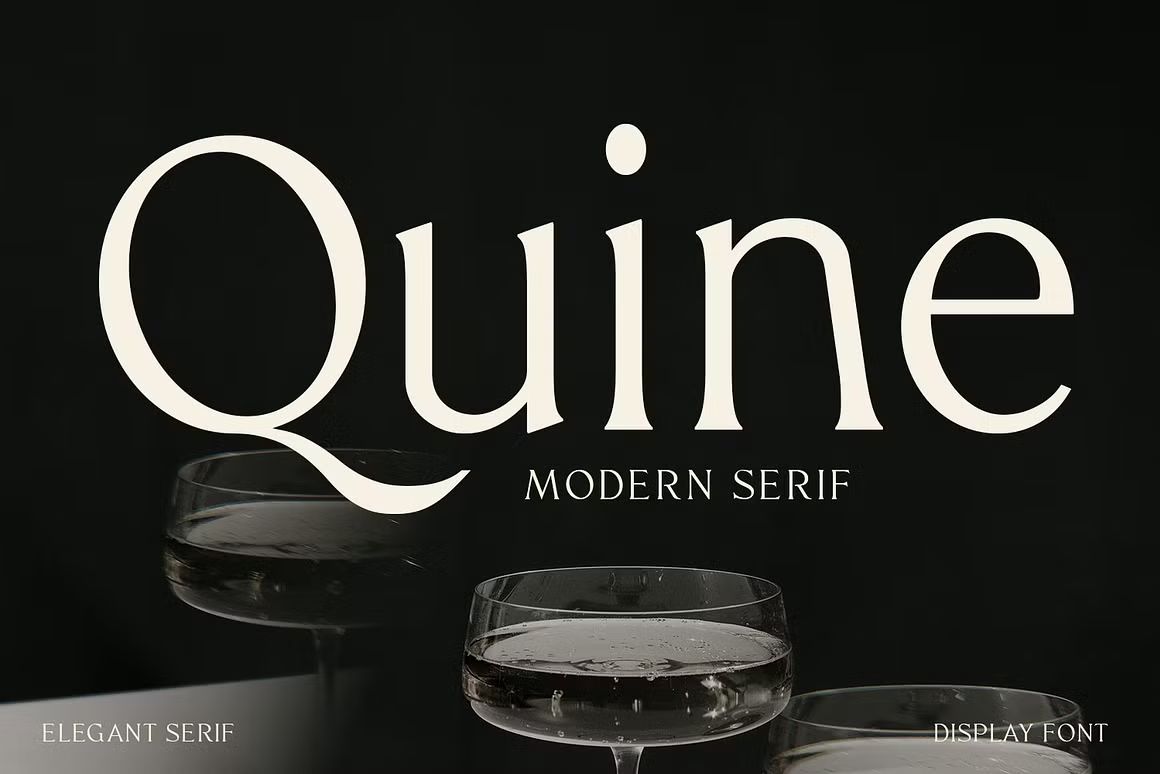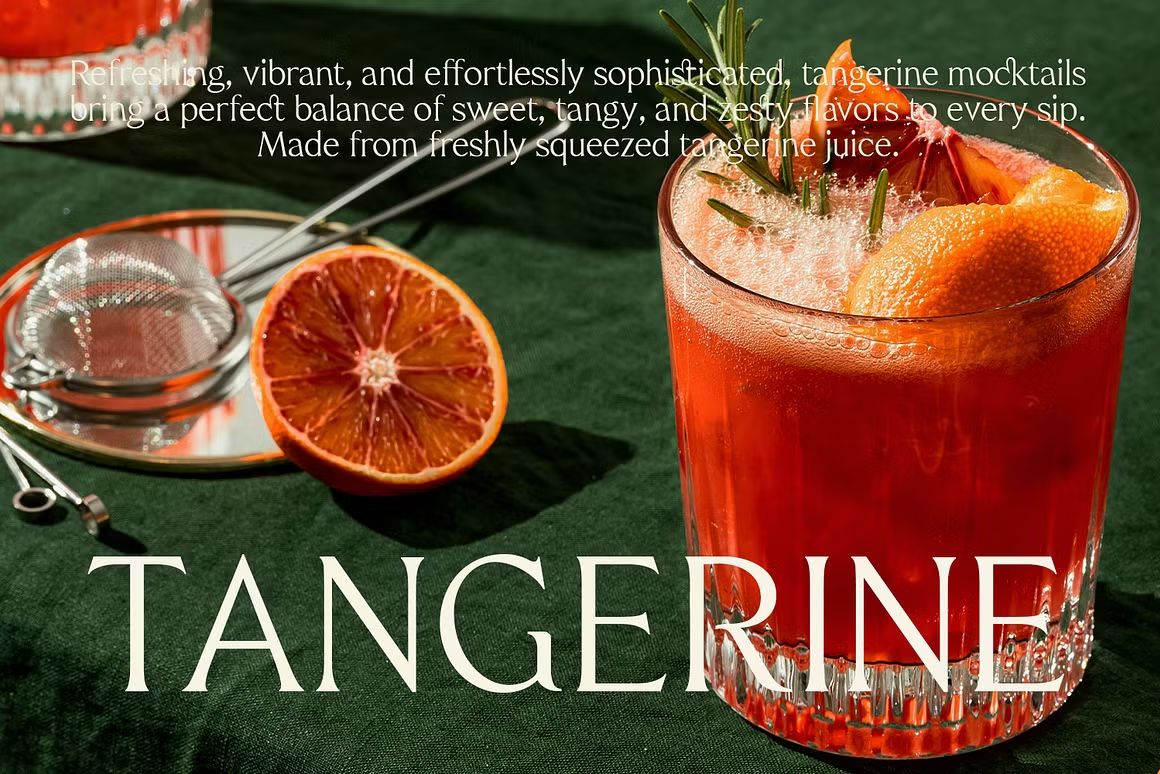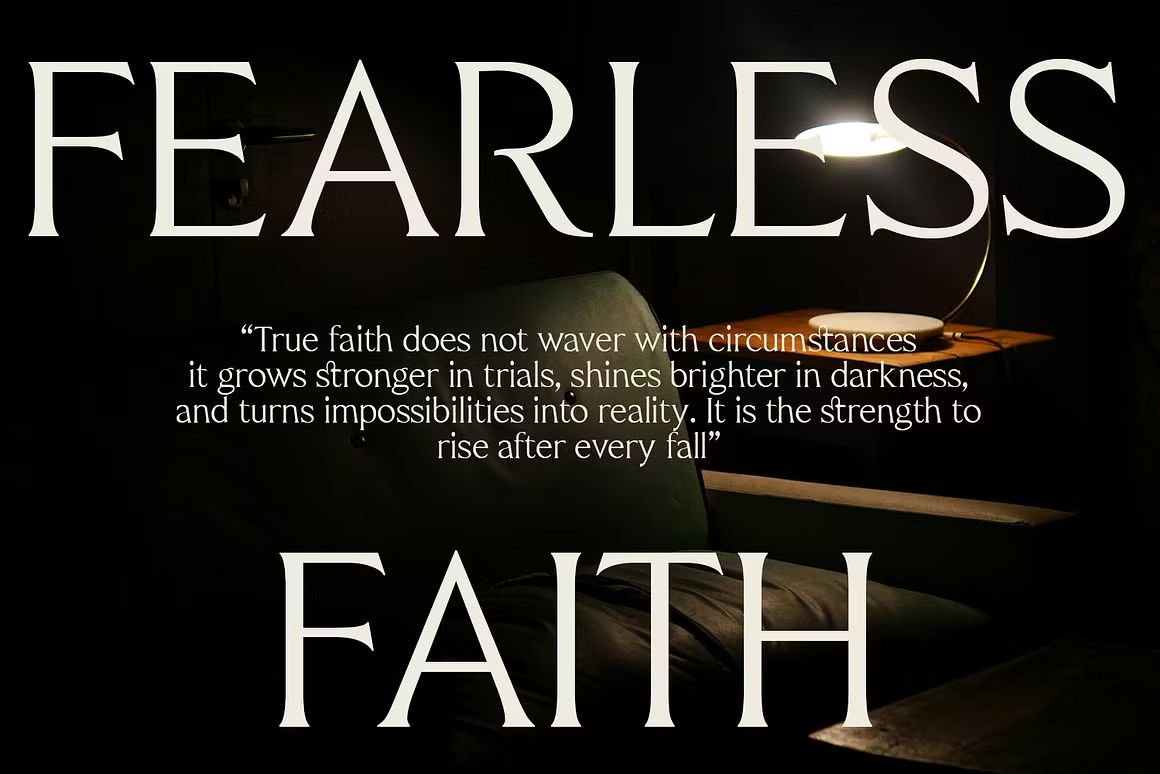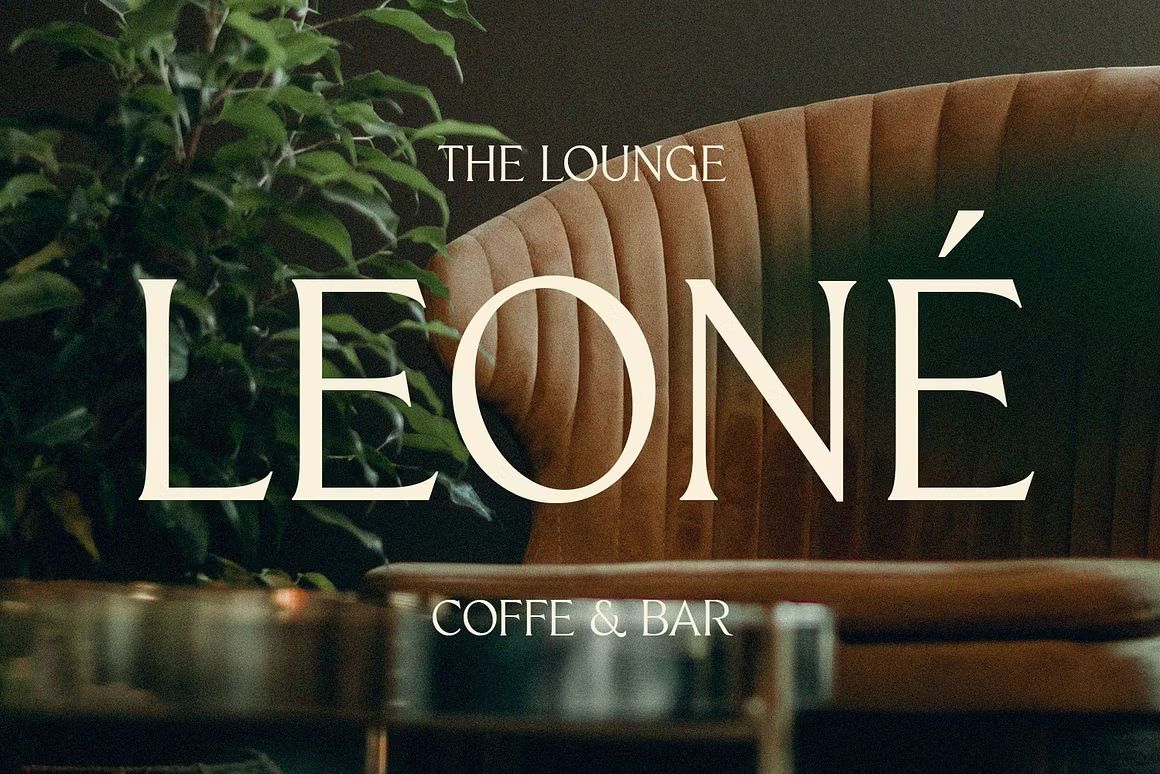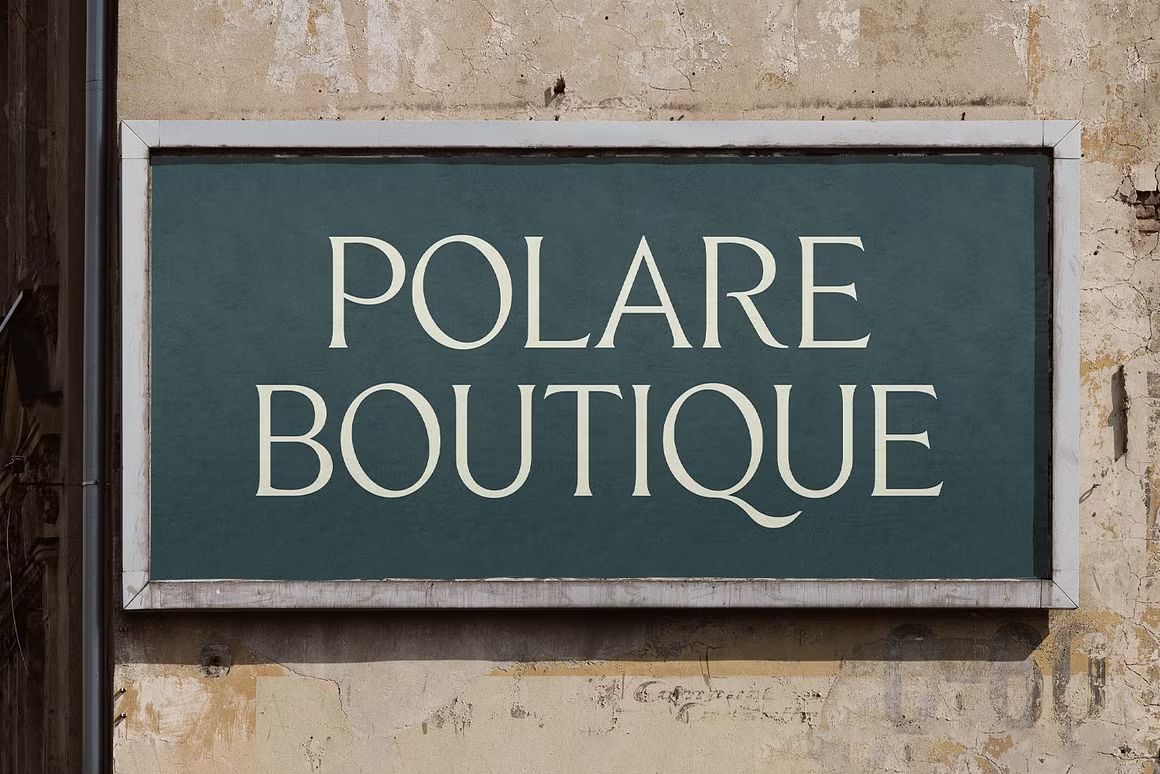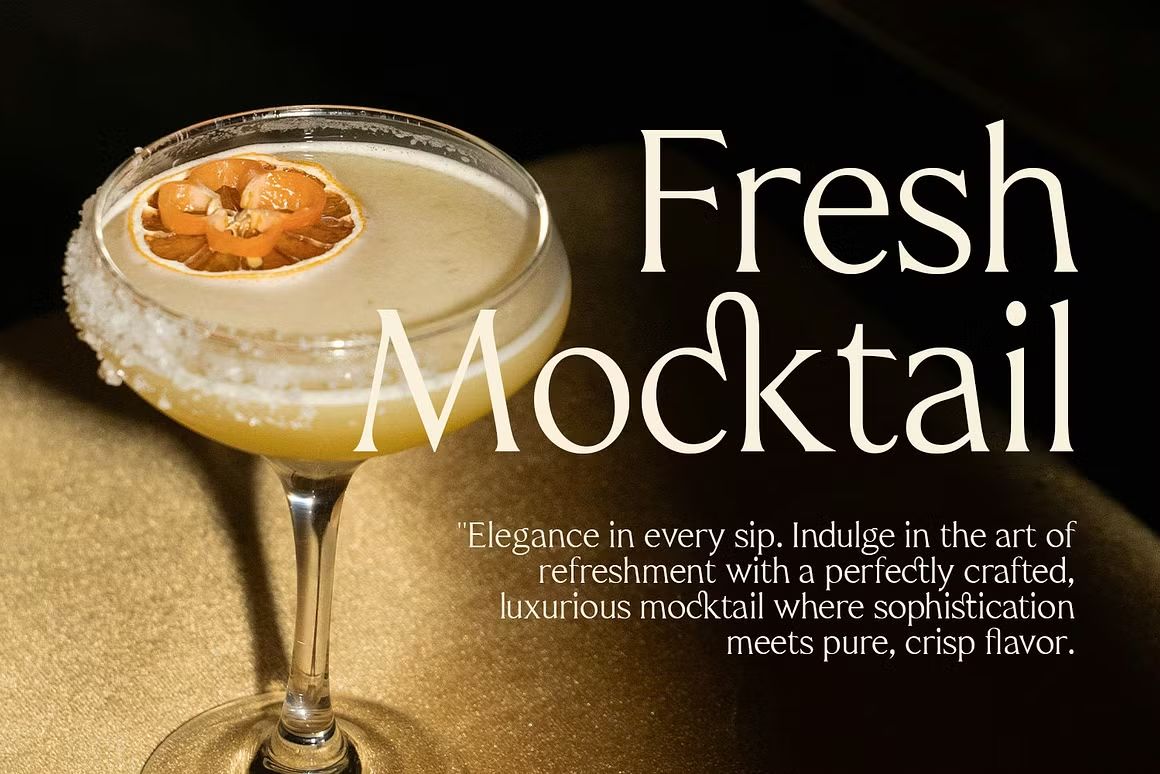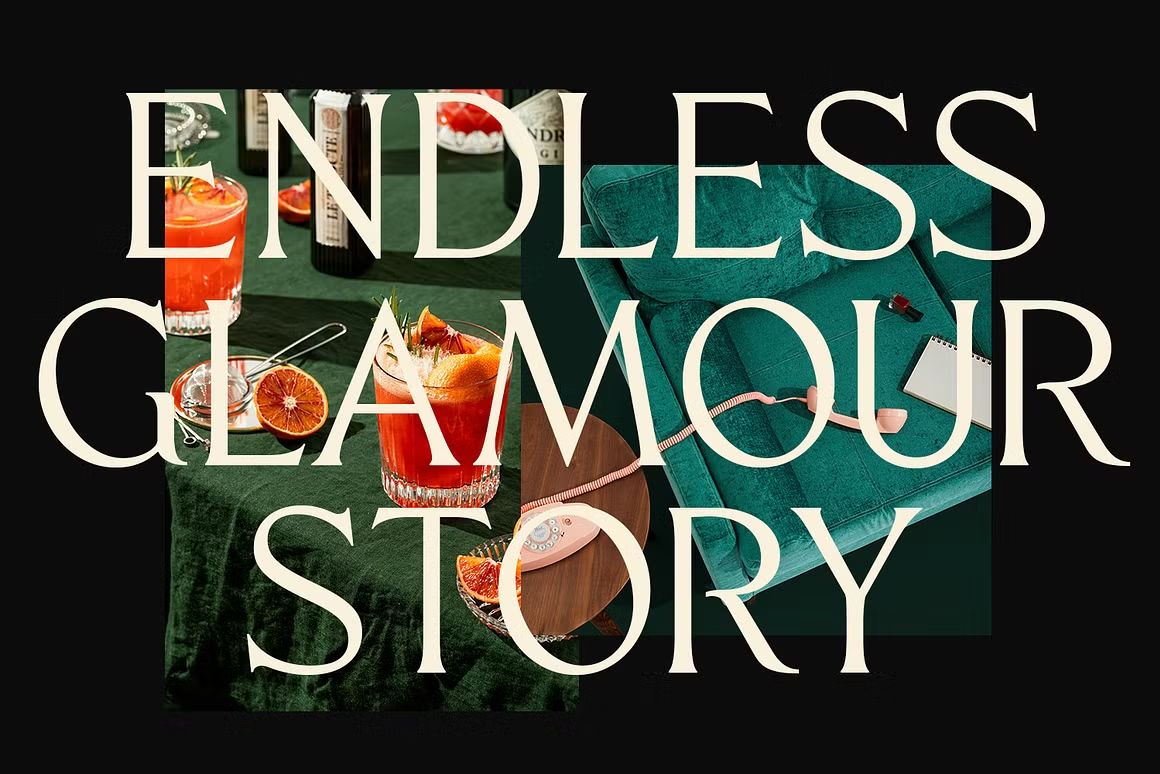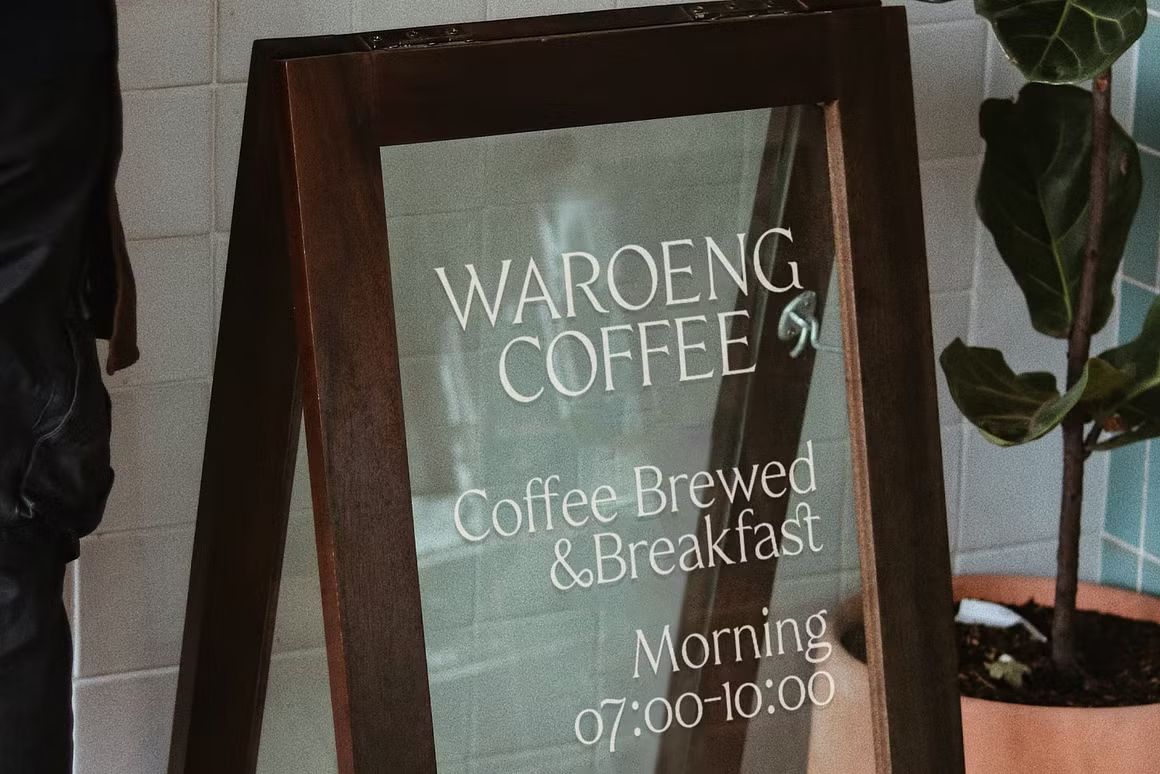
Quine – Sans Serif Font
Quine adalah font sans serif minimalis dan elegan, cocok untuk branding dan desain profesional. Format OTF/TTF/WOFF, siap digunakan.
Quine adalah font sans serif modern dengan desain minimalis dan proporsi yang seimbang. Karakternya bersih, tajam, dan mudah dibaca, menjadikannya pilihan ideal untuk berbagai kebutuhan desain seperti branding, editorial, UI/UX, kemasan, dan presentasi profesional. Tampilan Quine memadukan kesederhanaan dan fleksibilitas dalam satu gaya tipografi elegan.
• Sans serif modern dan minimalis
• Ideal untuk branding, desain digital, dan editorial
• Termasuk huruf kapital, kecil, angka, dan simbol